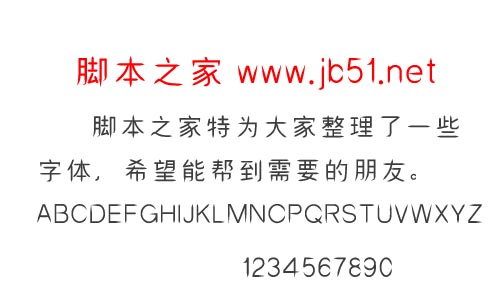
邯鄲雙劍體是邯鄲字庫(kù)推出的一款非常漂亮的藝術(shù)字體,風(fēng)格比一般的字體更有特色,連貫字跡顯得干練而不凌亂,清新簡(jiǎn)明,具有很好的視覺感,適合應(yīng)用于藝術(shù)設(shè)計(jì)、平面宣傳設(shè)計(jì)、網(wǎng)頁(yè)設(shè)計(jì),書法字帖等領(lǐng)域,歡迎喜歡邯鄲雙劍體的朋友前來(lái)下載使用。